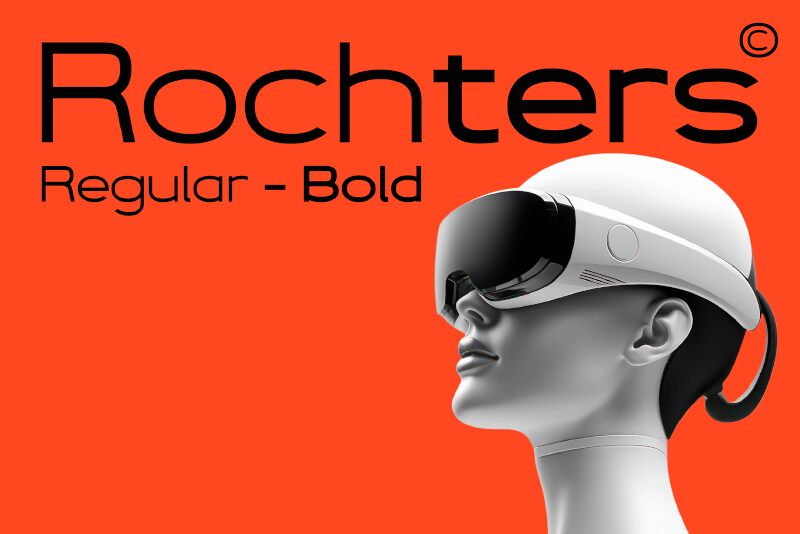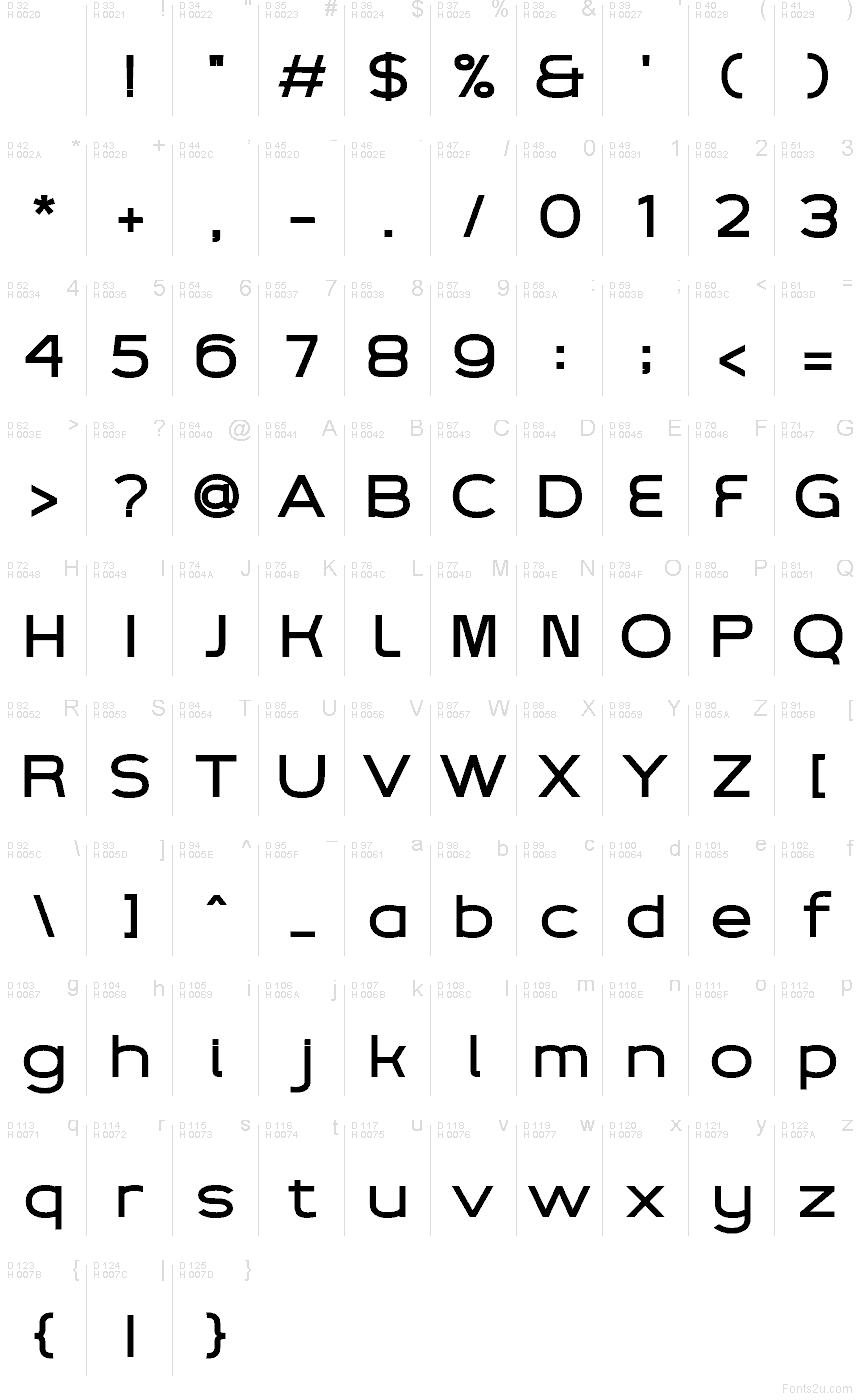
Rochters Bold par Glyphminds Studios est une police sans empattement géométrique gratuite au rythme épuré et moderne. Les lettres s'appuient sur des formes rondes généreuses et des jonctions ouvertes et simples, tandis que le « t » élancé et le « r » direct évitent à la police de paraître froide ou purement mécanique.
Cette police gratuite s'adapte aux systèmes de branding, aux en-têtes d'applications, au packaging, aux titres éditoriaux et aux affiches où vous recherchez une tonalité calme et contemporaine plutôt qu'un effet visuel bruyant. Elle fonctionne également très bien pour la signalétique courte ou les titres de cartes, car ses formes rondes rendent le lettrage uniforme et harmonieux sur toute la ligne.